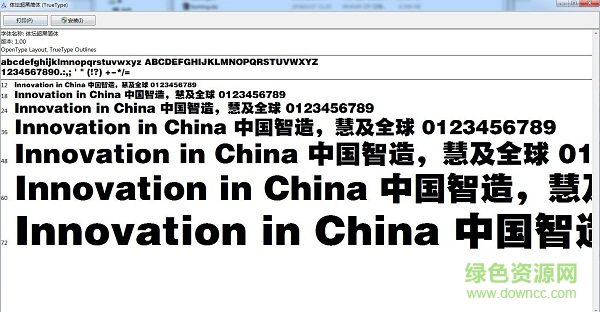
方正體壇超黑簡體是一款穩(wěn)重簡潔的黑體字體,字形富有力量感,剛毅挺拔,字面飽滿,適合男性主題的海報(bào)和平面設(shè)計(jì),需要的朋友快來綠色資源網(wǎng)下載吧!
這款字體筆畫粗壯,負(fù)形平行、對稱,重心平穩(wěn),時(shí)尚、剛正、厚重,不但適用于各種便攜式屏幕,還適用于傳統(tǒng)印刷媒介,也適用于時(shí)尚類的雜志、廣告、包裝設(shè)計(jì)和影視作品。